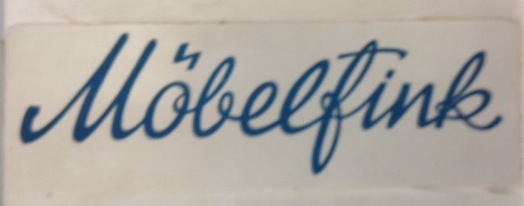
Schreibschrift- mitte 20. Jahrhundert 'Möbelfink'
Ähnliches habe ich schon gefunden. Allerdings fehlen dann immer die kleinichkeiten die die Schrift besonders macht. Die Firma gibt's garnicht mehr, und viel info auch nicht. Danke im Voraus.
Die unterschiedlichen Höhen der Anschlüsse und Verbindungen lassen nur den Schluss zu, dass es sich um ein gezeichnetes Logo und keine Satzschrift handelt.
Stimmt, der Querstrich ist eigenwillig. Als hätte der Schreibende zwei unterschiedliche f-Formen miteinander verquickt.
Sehr gut möglich, dass der Grafiker, der damals den Auftrag hatte, das Firmenlogo zu gestalten, sich an der Unterschrift des Auftraggebers gehalten hat, und daher dieser seltsame Strich im f kommt.
ich denke auch das es ein handgeschriebender schriftzug ist. bei einem f habe ich den strich aber auch noch nie gesehen, idenke auch das ist eine eigenwillige fi-ligatur. ähnliche formen gibt es z.b. bei den t-formen der metroscript.
Formal ist der Strich eine Verbindung zwischen l und i – welchen Sinn das ergeben soll, erschließt sich mir aber nicht.
Ich glaube eher, dass es sich hier um eine Art "angedeutete Binnenmajuskel" ist, welche den N amen Fink hervorheben soll. Vielleiocht hat Herr Fink das in den Vorentwurd sogar selbst hinein gema<lt, und wollte eigentlich MöbelFink, doch der Grafiker hat das dann nicht so verstanden oder wollte das so nicht umsetzen.
Ich glaube eher, dass es sich hier um eine Art "angedeutete Binnenmajuskel" ist, …
Aber dann hätte der Strich gerade nicht den Schwung des l aufnehmen dürfen, so verbindet der Strich ja mehr.
Drum meine ich ja:
1. Grafiker erstellt Skizze "Möbelfink"
2. Herr Fink bekommt die Skizze, will aber lieber "MöbelFink" und korrigiert das mit dem Strich in die Skizze hinein.
3. Grafiker bekommt Skizze zurück, erkennt den Wunsch aber nicht, und baut den überflüssigen Strich in die Reinzeichnung. "der will das ja wohl so"  als das Fertig war, war der Herr Fink nicht greifbar und ein Mitarbeiter nicht das ab...
Interessant. Habt ihr paar vorschläge die das gesamte ähneln?
Mir ist die fi Ligatur nicht so wichtig als das gesamt bild.
Das umlaut find ich super, könnte ich aber mit photoshop hin bekommen.